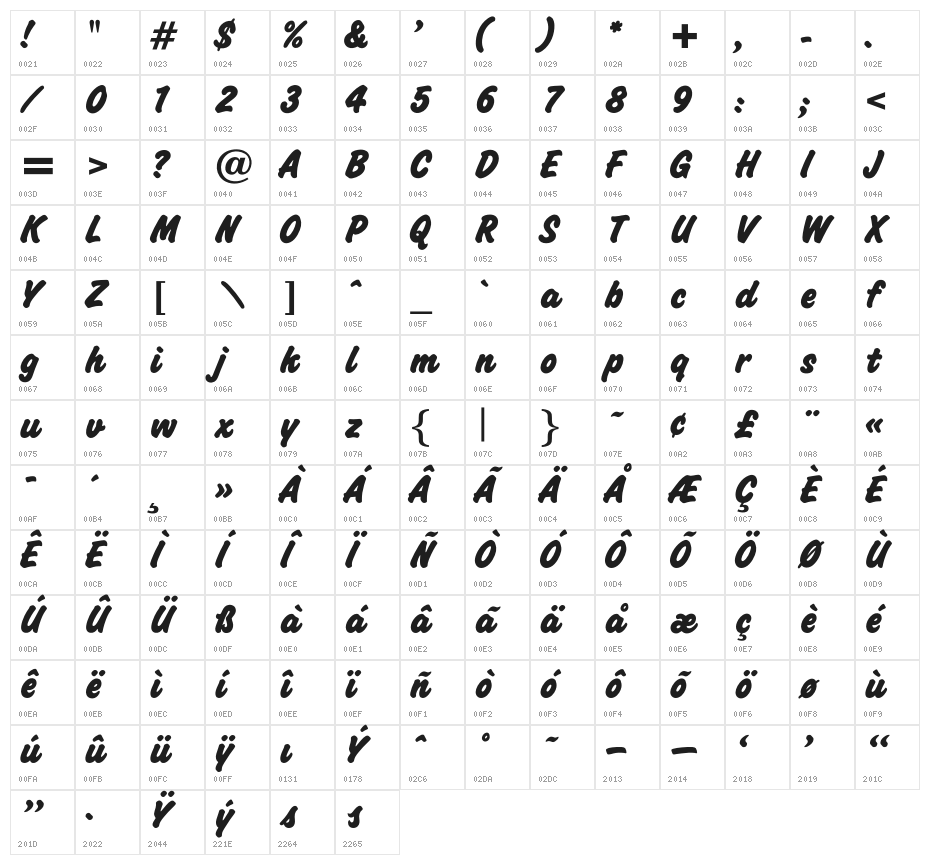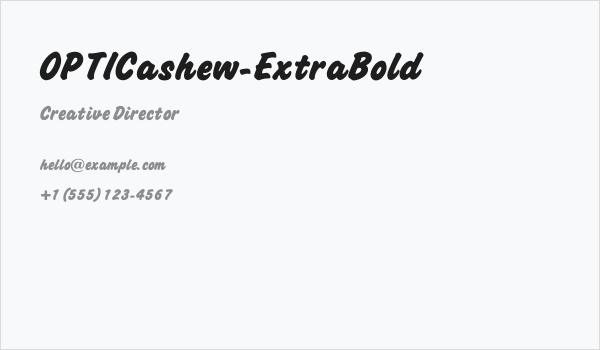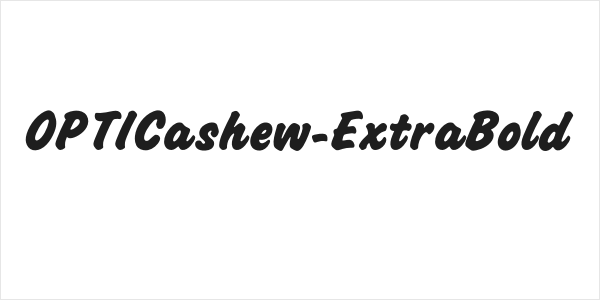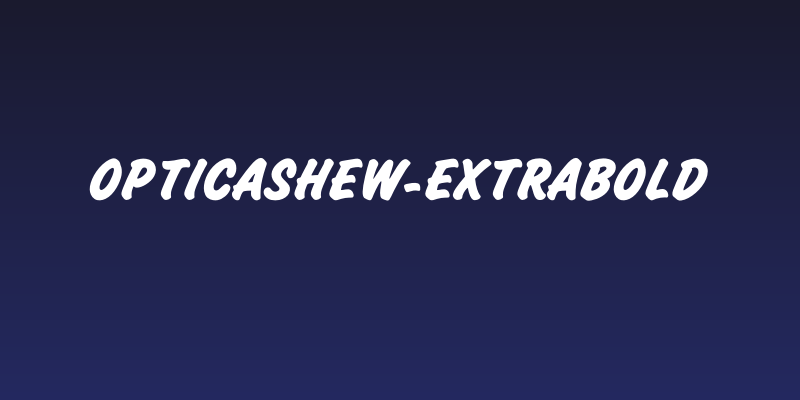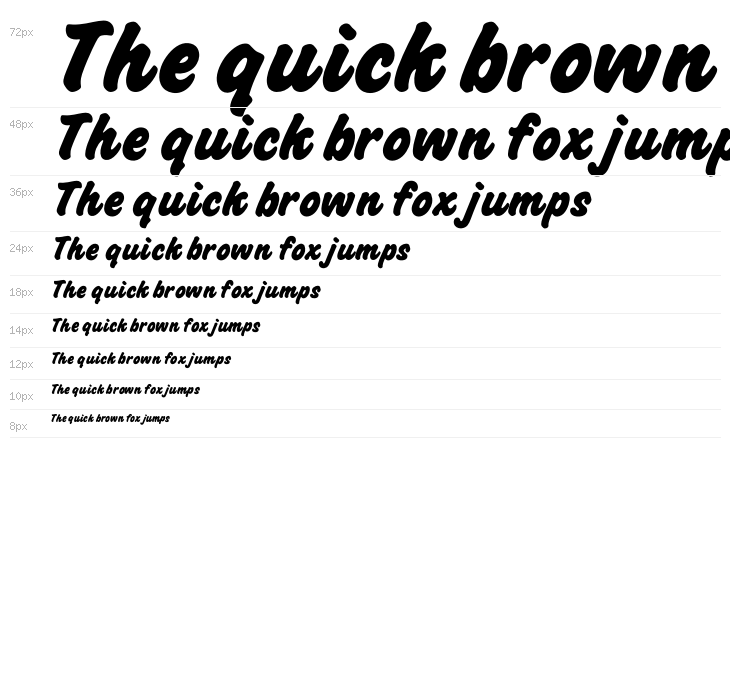
OPTICashew-ExtraBold Font
| Stil general | Playful and dynamic |
| Proiecte propuse | Ideal for branding, advertising, posters, and any project that requires a bold and energetic typeface. |